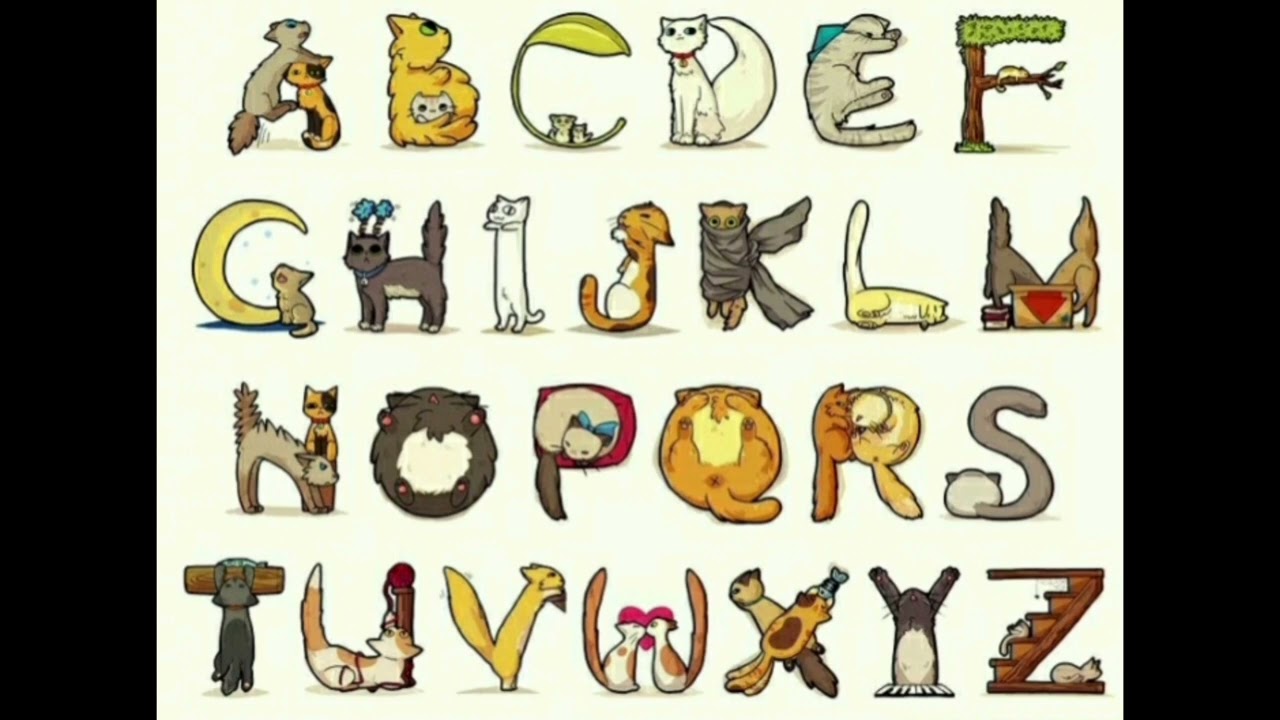
ОСОБЕННОСТИ ПОСТРОЕНИЯ ШРИФТА ПРИ ОБУЧЕНИИ СТУДЕНТОВ
В процессе работы со студентами отделений Декоративно-прикладного искусства и Педагогического образования факультета ИЗО и НР МГОУ, при изучении предметов «Проектирование», «Художественное оформление в образовательном учреждении», «Проектная графика», возникает необходимость освоения принципов построения шрифта и шрифтовых композиций.
Данные дисциплины призваны изучить и освоить различные приемы выполнения проектных и художественно оформительских работ, научить применять в своих работах разнообразные техники и способы графического изображения, научить выражать проектные идеи средствами и приемами графики, развить творческие способности, «…умение довести до зрителя смысл через художественно-выразительные средства, которые существуют в виде рисованных, печатных, экранных и объемных шрифтов, используемых в различных формах» [1]. «Шрифт – это исторически сложившаяся система знаков. Главное достоинство шрифта его удобочитаемость, но удобочитаемый шрифт совсем не обязательно является красивым Современный графический дизайнер или разработчики шрифтов, проектируя, опираются, прежде всего, на исторические особенности, характеристики, отличительные черты группы шрифтов и на свое чувство гармонии.
Во все эпохи в культуре письма, человеком отображались характерные черты, свойственные данному времени. Это стремление особенно ощутимо в развитии форм антиквы. Лучшим образцам средневековых рукописей свойственна тщательно продуманная форма, удовлетворяющая высоким требованиям удобочитаемости.
Искусно оформленный, он выполняет свою задачу намного лучше, чем шрифт из букв-схем, лишенных всякого эмоционального наполнения. Несмотря на то, что в некоторых исторических стилях шрифт был перенасыщен фантастическими дополнениями, всегда было заметно стремление к согласованности между основной целью – читабельностью и художественным оформлением. Если современному человеку сейчас трудно и утомительно разбирать старинное письмо, из этого не следует, что и его далекие предшественники испытывали такие же затруднения. Просто к современным шрифтам и старинным рукописям нельзя подходить с одной мерой удобочитаемости. Заслуги каллиграфов в разные исторические эпохи следует оценивать по тому, что они дали нового по сравнению с предшественниками.
Существуют различные стили, изображения шрифтов. Декорирование букв, не изменяя их основной формы (графемы), еще увеличивают шрифтовое богатство. В декоративном шрифте он может быть заштрихован белыми параллельными линиями, или заполнен орнаментами, или может представлять собой линейный контур с оттенением. Пользуясь особыми приемами, необходимо следить, чтобы шрифт не удалился слишком от общепризнанных норм. «Картинный» шрифт (например, в рекламе) дает некоторую информацию о содержании текста еще до его прочтения. Написанный или нарисованный шрифт любого стиля должен быть композиционно целостным.
Разработка шрифтовой композиции – вопрос авторский, подход к ее созданию индивидуален. Неясная и непривлекательная композиция не вызывает у зрителя интереса к прочтению. К размещению строк и расчету межстрочного пространства необходимо относиться с таким же вниманием, как и к рисунку самих букв. Изучение работ признанных мастеров шрифта помогает развить композиционные способности и подготовиться к самостоятельной творческой работе.
С другой стороны, трудно выполнить рукописным шрифтом короткий текст на большой поверхности.
При выборе техники наряду с назначением текста учитываются также его содержание и объем, образ и т. д. Очень распространена смешанная техника, при которой более важная часть – рисуется, а менее существенная, а значит и более мелкая часть – пишется пером или кистью. Реже встречаются буквы, выполненные обеими техниками совместно. Такая манера дает интересные возможности для художественного оформления шрифта главным образом при декоративных надписях и инициалах.
Когда намеченный текст размещен правильно, приступают к более точной прорисовке букв карандашом. Лишь после этого можно выполнять шрифт тушью или краской, или другими графическими материалами.
Большое влияние на рисунок шрифта оказывает инструмент, которым шрифт выполняется, а также материал и характер его поверхности. Букву можно написать или нарисовать пером или кистью, ее можно написать акрилом, гуашью, тушью, акварелью, темперой и т. д.
Уже на эскизной стадии необходимо продумать цветовое решение, которое должно соответствовать технологическим возможностям исполнения шрифтов определенного вида.
Когда цветные элементы композиции не соприкасаются друг с другом, шрифт может выполняться и одной краской. В этом случае на полях оригинала делаются пометки, какой краской надо выполнять каждую из частей композиции. Несмотря на то, что современные технические приемы работы с цветом вполне заменяют ручные, последние еще довольно распространены и отнимают у студентов много времени и труда. Облегчить работу может использование графического планшета.
Бумага для изображения шрифтов должна быть хорошего качества и плотной. Слишком мягкая бумага, которая под инструментом легко отделяет волокна, пригодна только для работы кистью. Наилучшими являются бумаги, изготовленные из качественного сырья (например, бумага «Гознак»). На зернистой и льняной бумаге хорошо получается шрифт, выполненный полусухой кистью. Свободные и размашистые заголовки удобно выполнять жирным карандашом или линером, маркером, которые не стираются в отличие от обычных графитовых карандашей.
Другие студенты иначе относятся к работе, на стадии карандашного эскиза более точно и продуманно, и тогда основная часть работы в творческом процессе приходится на эту стадию. При таком исполнении каждый мазок, проведенный краской, сразу приобретает законченный вид по форме и цветовой насыщенности и редко подлежит исправлению.